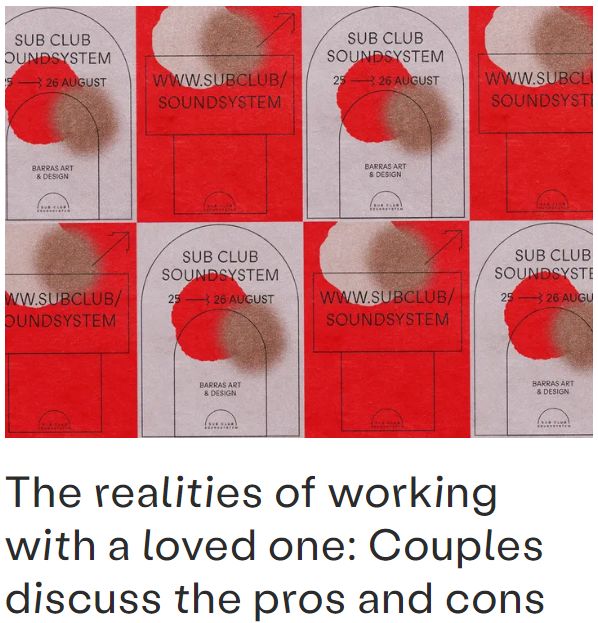
字体设计的未来,由正在加速进化的可变字体开启
2019年的下半年,“智能可变字体”(Variable Font)一词接连不断地出现在人们的视线中,引发了不少热议。
9月24日,小米发布了MIUI动态字体系统。随后不久,国际奥林匹克委员会在10月21日公布了2024年巴黎奥运会LOGO及定制可变字体“Paris 2024”。而蒙纳也在11月公布“2020年的5大字体趋势”,并预测了“可变字体的兴起”。
小米MIUI(上)和“Paris 2024”(下)
那么,可变字体的起源是什么?它是怎样被创造出来的?而承载可变字体的媒介又将会有怎样的发展?近日,创意网站It's Nice That采访了Dalton Maag字厂的创意总监Bianca Berning,与他一起回顾与展望可变字体的发展轨迹。
其实,“智能可变字体”并不是什么新颖的技术。早在上世纪90年代初,Adobe和苹果就基于Axis技术,分别研发了Multiple Master字体和TrueType GX字体。这两种字体也就是现今可变字体的雏形。
Multiple Master字体(上)和TrueType GX字体(下)
Berning解释道,到了2000年,Adobe放弃了Multiple Master字体的研发。同时,由于缺乏方便使用的开发工具的支持,TrueType GX字体的发展也受到阻碍。随后,Adobe决定与微软联合开发字体格式OpenType,以整合并取代TrueType GX字体。
直至2016年,在第60届ATypl研讨会上,苹果、Adobe、微软、谷歌以及Dalton Maag等独立字厂和字体设计工作室联合发布了OpenType 1.8版,将“OpenType Variable Fonts”引入扩展规范。可变字体就此正式面世。
“从那时起,字体设计师创造了数百种不同的可变字体。有些实验性的创作是为了探索这种技术的边界,而有的则具有极强功能性,目的是提高网页的性能。”Berning说。
在过去几年里,支持可变字体的软件不断增加和迭代。如今,可变字体的应用已经覆盖了电脑操作系统、主要的浏览器和应用程序,包括InDesign、Illustrator、Photoshop、Sketch等等。设计师们因此得以更方便快捷地了解和使用可变字体。
而Dalton Maag字厂则在2018年就发布了他们的第一款可变字体Venn。从那以后,他们又陆续发布了三个可变字体系列——Objektiv、Mokoko和Aktiv Grotesk。
“无论是极具表现力的粗体风格,还是简洁而具有强功能性的类型,可变字体都让设计师和其他使用者在文字的排版和处理上有了更大的发挥空间。”Berning表示,“这激发了我们对扩大可变字体库的热情,同时也带来了更多关于定制可变字体的讨论。”
Dalton Maag字厂的Aktiv Grotesk项目
那么,设计一套可变字体需要考虑哪些因素呢?和静态字体一样,每个可变字体项目都各不相同。因此,Berning认为第一步是要定义字体设计的整体需求。
一般来说,字体设计师需要考虑到客户使用字体的目的、字体所要表达的内容、获取字体的方便程度、字体的功能性以及所归属的语言系统等多个方面。而在设计可变字体时,还需要考虑字体样式和特征,调整字体结构的空间美感,同时设置字重(Weight)、字宽(Width)、视觉尺寸(Optical Size)、书写体(Italic)和斜度(Slant)五个轴参数。
如果客户要求比较简单,比如要设计一种能够屈伸以适应不同包装尺寸的标题字体(Display Typeface)时,设计师可以考虑处理字体的宽度轴,让字体能随意从最窄延伸至最宽的宽度。但如果要设计一个单独的可变字型,则应该考虑视觉尺寸的变量,包括比例调整、对比度和笔画权重等等。
从上至下:字重、字宽、斜度
Berning和团队选择将Aktiv Grotesk设计成可变字体,是因为它十分实用,整体给人一种理性中带有些许温暖的感觉,而这在Grotesque字体系列中很是少见。他们希望通过制作可变字体来提高Aktiv Grotesk的实用性。
由于可变字体格式智能地将整个字体系列的信息压缩到了一个文件中,比集合了所有单个字体的字体包还要小。设计师们可以在网页版面设计中应用不同的字重和样式组合,但不会影响页面加载时间,而且经济成本不会太高。
Dalton Maag字厂的Aktiv Grotesk项目
除了这些便于阅读使用的字体以外,近来也不断涌现出了许多有趣的可变字体设计。OHNO Type的Cheee字体被称为“高对比度团子”(High-contrast Blobber),它的可变形式促使设计师们去思考,除了标准的五个轴参数之外还有什么维度是可变的。
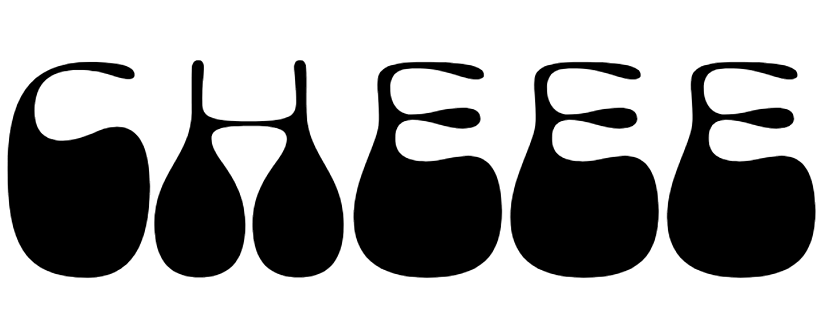
OHNO Type,Cheee字体
而字体设计师David Jonathan Ross则在上个月推出了Gimlet X-ray字体。这种字体极具实验性,它展示了可变字体的内部变化机制,人们可以拖动各种参数的轴线以感受字体的变化。具体应用请前往官网了解体验:
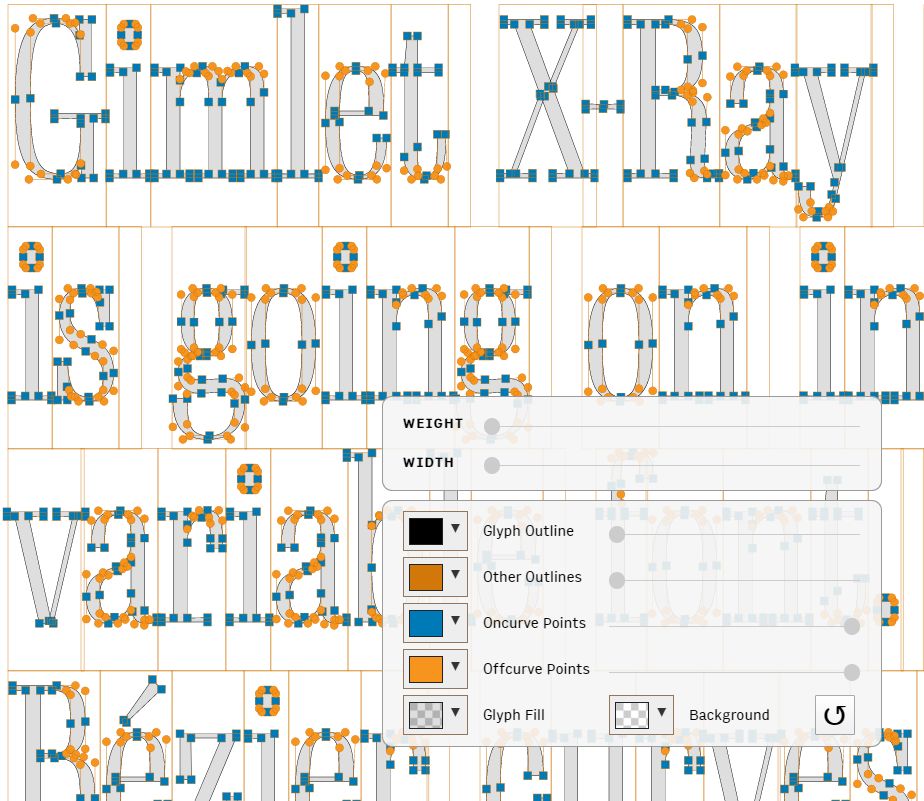
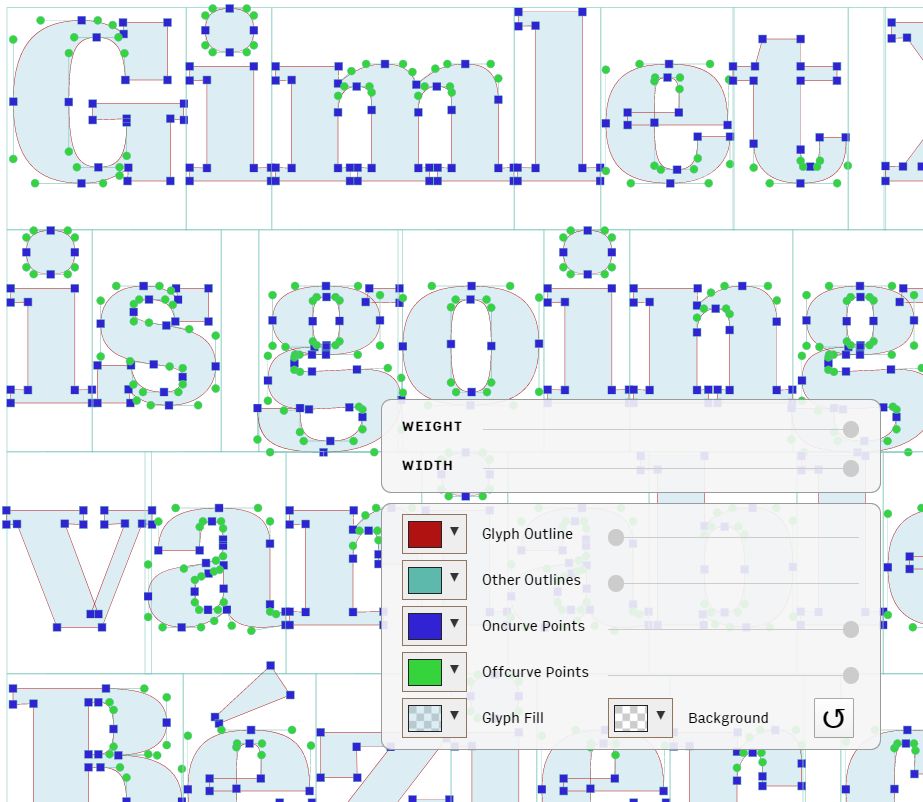
David Jonathan Ross,Gimlet X-ray字体
与此同时,可变字体的出现也改变了字体在设计项目中的应用方式。Berning认为,未来的设计也许会更注重于字体,而不是单单依赖于图像等视觉元素。设计师们能创造更多不同的视觉变化,在数字环境中探索多样的排版布局和更好的阅读体验 ,同时不必担心延长了加载时间。
Studio Feixen字体
若可变字体与大数据相连,它将会拥有更强的交互性。试想一下,字体的大小和样式随着灯光、噪音、温度、天气数据的不断变化而改变,这将会让信息传播和交流变得更高效。
“在过去的一年里,我们也看到了不少项目在探索可变字体的潜力。有的项目注重于表达,有的则更侧重于功能。”Berning回想道,“比如Dumbar工作室的‘Cities in Motion’公益运动就将可变字体作为广告海报的核心,创造了令人意想不到的效果,吸引了许多路人驻足观看。”
Dumbar工作室,“Cities in Motion”动态设计运动
而It's Nice That网站在升级之后,也应用了可变字体。每篇文章的标题都使用了LabilVariable字体,使标题字可以根据文章内容基调的不同,有一些轻微的改变。
It's Nice That网站将可变字体应用于标题
在Berning看来,随着越来越多人熟悉了这个技术及其优势,将来会出现更多的实际应用。比如只在网页中嵌入一个字体文件,让网页框架更简单干净。又或者是让字体根据读者的年龄和距离屏幕的远近,进行尺寸的调节。
“如今,我们只是探索了可变字体在交互性和沉浸感方面的应用,这只是皮毛。但随着技术的普及,越来越多主要平台都将完全支持可变字体。这同时也会促使人们进行更多实验性设计,促使可变字体进一步升级。”Berning对此很有信心。